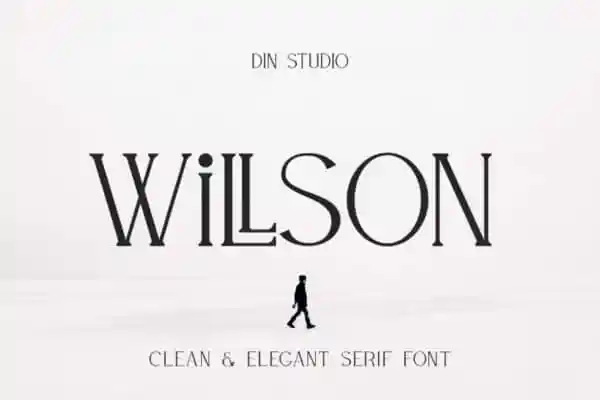
Willson Serif Font – Download Grátis
Olá! Introduzimos a Willson Serif Font, uma tipografia serif que oferece contraste visual mas mantém uma beleza refinada. Desenhada pelo designer Din Studio, esta font é projetada para um estilo moderno e limpo. A Willson Serif é ideal para complementar seus designs de marca, logotipos, impressão e vários outros usos. Seja em suas campanhas digitais ou sua presença nas redes sociais, a Willson Serif é uma escolha perfeita. Ela adicionará um toque especial aos seus trabalhos digitais e físico, seja para branding, logos ou qualquer aplicação de design impressão que você possa imaginar. Essencialmente, a Willson Serif oferece mais do que apenas uma fonte; ela traz ao seu projeto uma sensação sofisticada e elegante. Aproveite-a em suas próximas criações para dar um toque autêntico e único à sua marca ou produto digital.